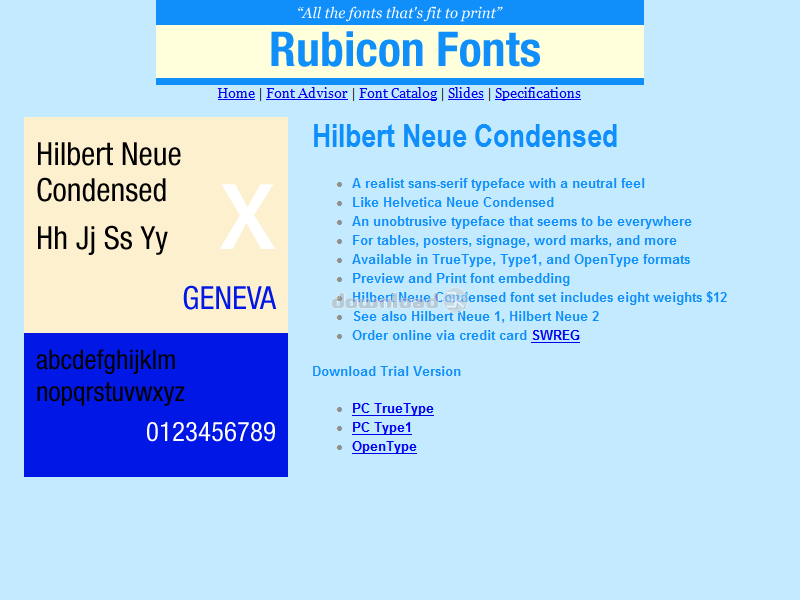
"Realist sans serif font, neutral feel"
Condensée réaliste sans serif avec une sensation neutre. Comme Helvetica Neue Condensed. Une police de caractères discrète qui semble être partout. Monter plus de texte dans des espaces restreints, sans perdre la lisibilité. Idéal pour les tables, affiches, panneaux, et autres documents graphiques. Précis et laissé entendre, ce qui correspond mesures de police, jeu de caractères standard, crénage paires. Qualité dimpression professionnelle pour jet dencre, laser, typographe à 3500 dpi. Les acheteurs reçoivent 8 variantes de police comme suit: Light, Light Oblique, Normal, Oblique, Bold, Bold Oblique, ExtraBold, Extrabold Oblique.Exigences: Older versions of Windows require Adobe Type Manager.